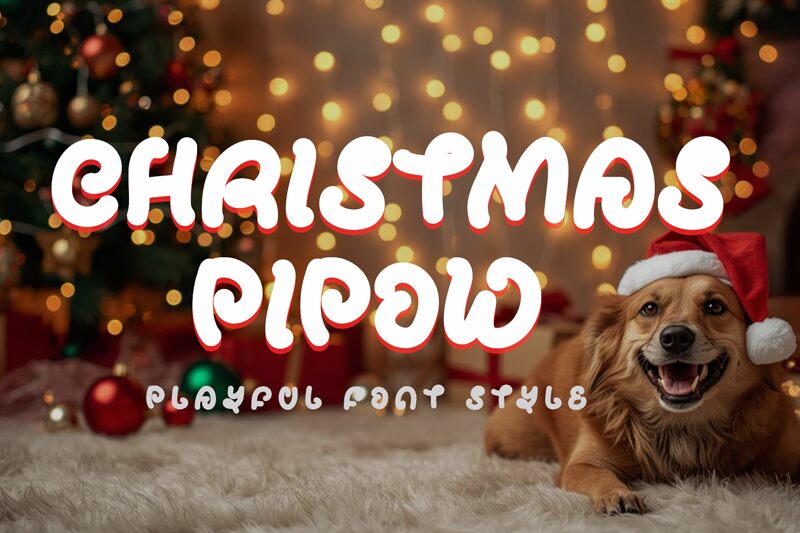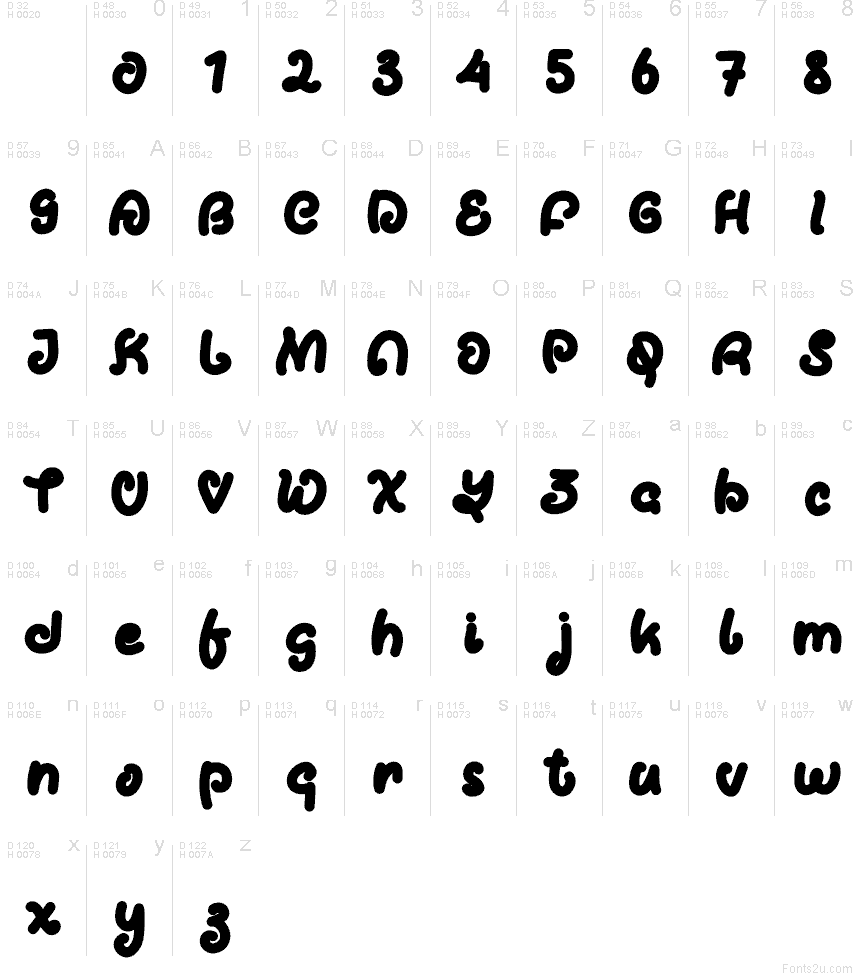
Christmas Pipow Demo
Christmas Pipow - это бесплатный праздничный шрифт с округлыми мультяшными формами и мягким, игривым ритмом. Буквы выглядят плотными и неформальными, а плавные изгибы и компактные соединения придают любому заголовку радостный новогодний вид.
Christmas Pipow - это бесплатный шрифт, который отлично подойдет для новогодних открыток, праздничных плакатов, бирок для подарков, баннеров, приглашений и графики для социальных сетей. Его округлые формы идеальны для коротких декоративных надписей, где важнее создать теплую и дружелюбную атмосферу, чем набрать длинный текст.